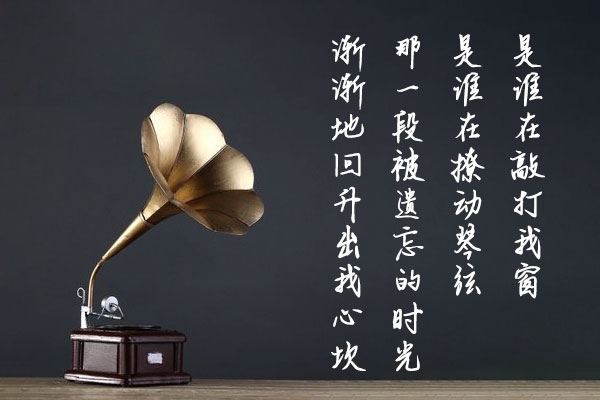
千图纤墨体
千图纤墨体:古韵与现代设计的完美融合
千图网推出的千图纤墨体是一款免费商用字体,它的设计灵感来源于古代书法家的书法艺术。这款手写字体以其纤细而有力的字形和自然流畅的运笔,展现出独特的艺术风格。字间距紧凑,使得页面更显饱满和丰富,极具视觉吸引力。
千图纤墨体适用于清新海报、影视和综艺类设计,为你的作品增添一抹古韵与现代设计的完美融合。无论是在标题设计还是长文排版,千图纤墨体都能发挥出其独特的魅力,使文字成为视觉焦点,引人入胜。